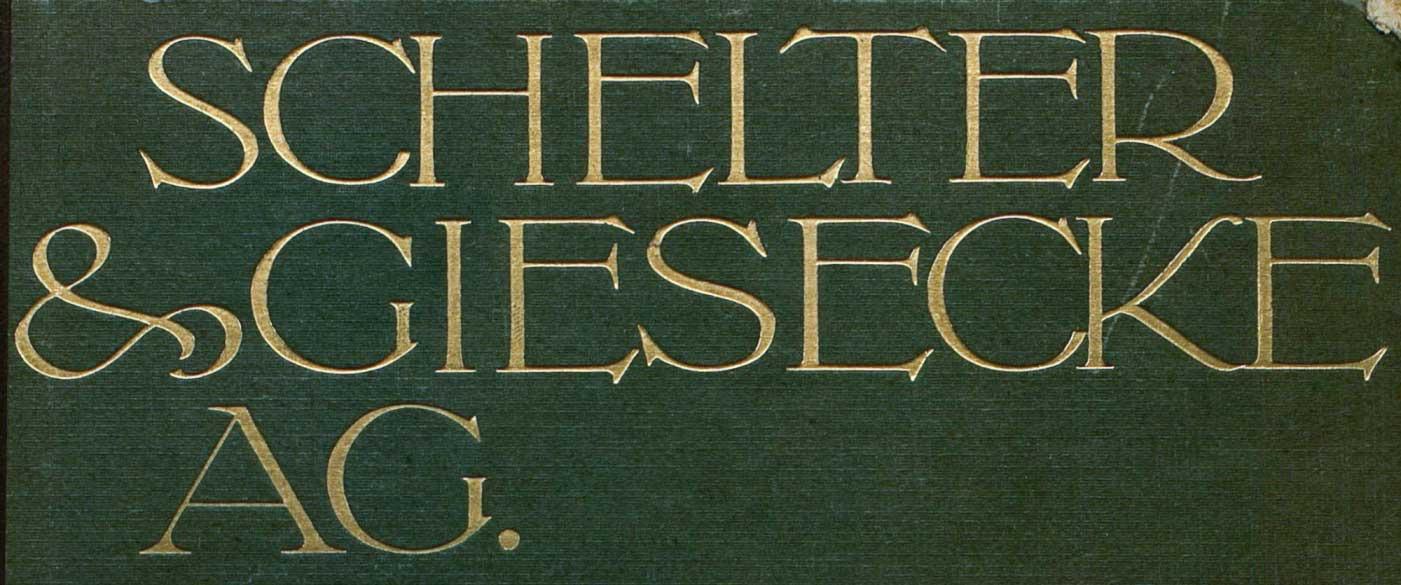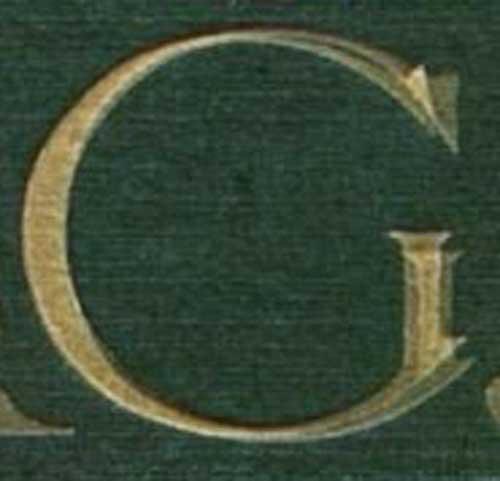
Name einer Schrift auf Cover der Hauptprobe. J. G. Schelter & Giesecke, Leipzig
Mir ist direkt die Schrift auf dem Cover aufgefallen und trotz umfänglicher Recherche konnte ich sie leider noch nicht zu ordnen. Hat zufällig jemand eine Idee welchen Namen sie trägt?
Ich würde auf eine extra angefertigte Zeichnung tippen, die dann als Messing-Klischee für die Buchbinder angefertigt wurde.
Druckschrift ist es mit Sicherheit nicht. Bleibuchstaben können nicht so eng stehen. Und bei einer Präge-Schrift dürfte es solche Unterschiede nicht geben: